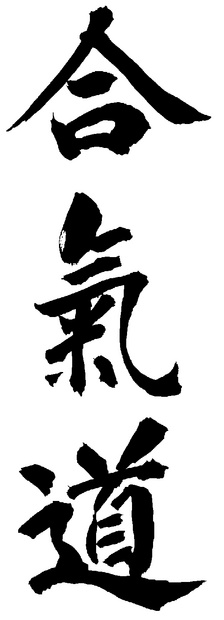
Schrift für Visitenkarten
ich suche für meine Visitenkarten eine Schrift die zu Kanji passt und die unter GPL läuft.
Sie soll auf jeden Fall seriös wirken. Ich habe schon um die 40 Schriften aus probiert, und mir gehen die Ideen aus.
:kopfkratz: Ganz so simpel ist das leider nicht ... Sollen es denn Visitenkarten werden, also private Karten mit Deiner Rufnummer, oder Geschäftskarten? In jedem Fall hängt die Wahl der Schrift in erster Linie davon ab, wer Du bist und was Du mit dieser Karte und ihrer Gestaltung vermitteln möchtest. Idealerweise kommt die Frage nach den technischen Möglichkeiten (also beispielsweise Schriften die zueinander passen) erst an zweiter Stelle. Das ist aber natürlich schwieriger, wenn man durch den Wunsch nach einer kostenlosen Schrift zusätzlich eingeschränkt ist ... :-)
Außerdem stellt sich die Frage, was Du mit Kanji meinst. Ich gehe davon aus, dass Du chinesisch-japanische Schriftzeichen meinst, also die abgefahrenen Teile, die weder Hiragana noch Katakana sind ... In denen wird im Japanischen normalerweise aber kein Text aus einer westlichen Sprache gesetzt, also beispielsweise Dein Name und Deine Adresse, sondern in Katakana, so weit ich weiß ... Und in jedem Fall gibt es ja auch viele verschiedene Katakana- und Kanjifonts ... Wenn man also Deine Frage ganz simpel beantworten wollte, müsste man wissen auf welchen Font Du Dich beziehst ... :-? Aber wie gesagt, die Methode führt eigentlich nicht zu einem vernünftigen Ergebnis ...
Was mir Tante g unter Kanji bei Adobe anzeigt, sieht recht "authestisch handgemalt" aus. Für fremdländisches generell eignet sich die Gill Sans manchmal ganz gut.
GPL? Vielleicht gibt es die Gill Sans da irgendwie auch .…
... eine Schrift die zu Kanji passt ...
Da auch Kanji / chin. Zeichen, also keine Kana / in nicht nur einem Font existieren, müsste man vielleicht zunächst einmal wissen, welche Schrift du dort zu verwenden gedenkst. Dann kann man was empfehlen.
Aber schnell zurück zum Thema: Ich könnte mir zu Kanji-Schriftzeichen gut eine sehr dünne Futura vorstellen.
Es wäre aber hilfreich, wenn wir wüssten, wie der Kanji-Font aussieht, der in diesem konkreten Beispiel verwendet werden soll.
… Sie soll auf jeden Fall seriös wirken. …
Auf Europäer oder auf Fernostler?
Ich glaube ich habe zu wenig Details aufgeführt.
Zunächst bin ich Trainer einer Budo-Sportart und das in 3 Vereinen des weiteren gebe ich in dem Sport auch noch Kurse.
Es soll auf Europäer als auch auf Asiaten seriös wirken.
Im Anhang findet Ihr die entsprechende Kalligrafie.
Ich frag einfach mal:
1. Ist das eine private Visitenkarte, die mit einigen Kanji verziert wird, weil sie andeuten soll, was Du hobbiemäßig machst, oder geht es um eine Geschäftskarte, die tatsächlich für Dich werben soll, weil Du entweder Dein Hobby sehr ernsthaft betreibst oder sogar das Lehren zu Deinem Hauptberuf machen möchtest?
2. Sind die Kanji eine Verzierung oder eine Art Logo, oder soll eine typische zweisprachige Karte entstehen, Vorderseite lateinische Lettern, Rückseite Kanji?
3. Wie siehst Du denn Dich, und wie Deine Sportart (oder Kampfkunst?); was willst Du dem Betrachter vermitteln? Bist Du ein Sportlehrer? Ein Selbstverteidigungslehrer? Oder gar jemand der auch eine philosophische Sichtweise der Dinge vermittelt? Und wer kommt zu Dir? Sportler, Selbstverteidiger oder kämpfende Philosophen?
4. Was kannst Du Dir später im Druck leisten? Das beeinflusst ebenfalls, wie schlicht (seriös) so eine Karte gestaltet werden kann, ohne dass sie im Endeffekt vielleicht billig wirkt ... :-D
Folgende Schriften könnten gut passen, da sie recht schwungvoll sind und der Handschrift (Kalligraphie) nahestehen:
Gentium, Neuton, Fontin.
Du könntest natürlich auch auf mehr Kontrast setzen und, wie Kathrin schon vorgeschlagen hat, eine magere Grotesk benutzen. Vorschläge:
Andika, Aller Sans, Pigiarniq, M+ Fonts, Droid Sans, Lacuna, Mr Jones, Museo Sans, PT Sans, Eau Sans.
Wenn keine anderen Zeichen als 合气道 mehr auftauchen, dann nimm was serifenloses, möglichst geometrisches(sparsames. Und bitte keines falls s p e r r e n oder senkrecht schreiben ;-)
... nimm was serifenloses, möglichst geometrisches ...
Dem schließe ich mich an. Am besten auch noch einen leichten Schnitt als hohen Kontrast.
Z. B. Futura, Avant Garde oder auch Avenir.
Danke für Eure zahlreichen Rückmeldungen bin echt Überrascht wie viele hier mir antworten.:bow:
@ Minimalist
Zu 1 Ich betreibe dieses Hobby seit nunmehr als 24 Jahre und das immer intensiver.
Zu mir kommen Kinder, Jugendliche, Erwachsene und Rentner. Vom Hilfsarbeiter bis zum Akademiker ist alles vertreten.
Der Grund warum die Leute kommen ist so vielfältig, dass es den Rahmen hier Sprengen wird.